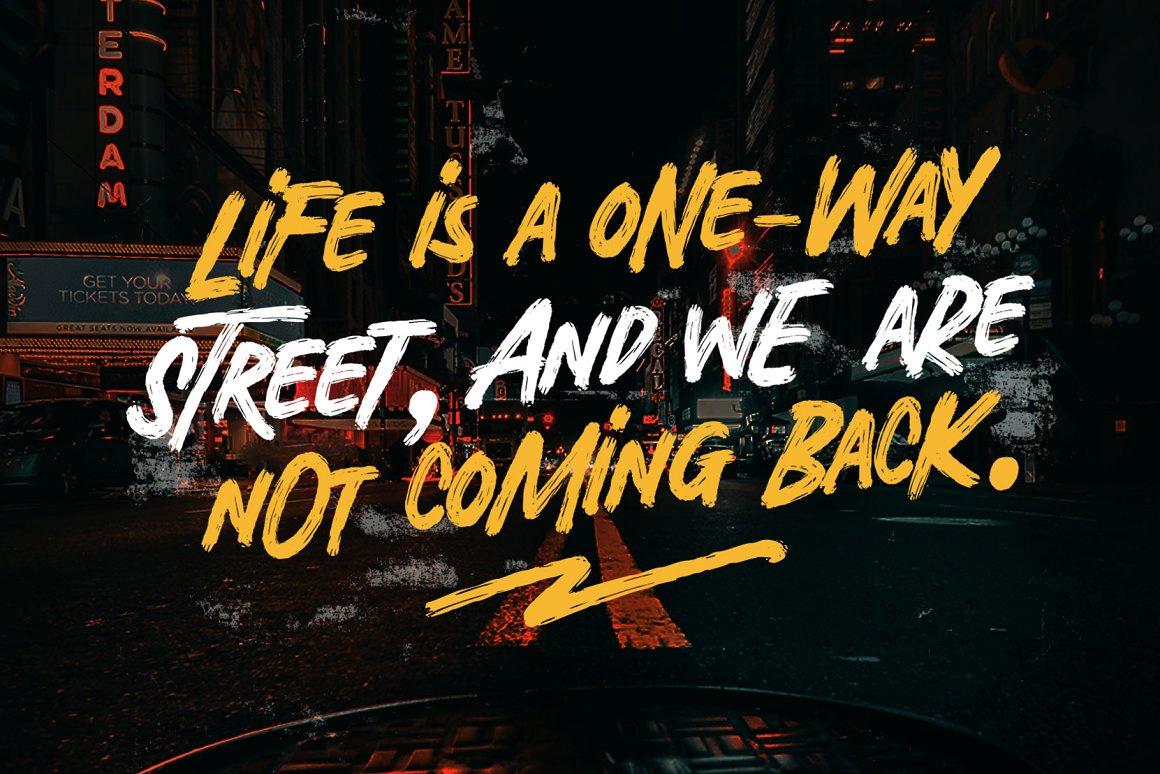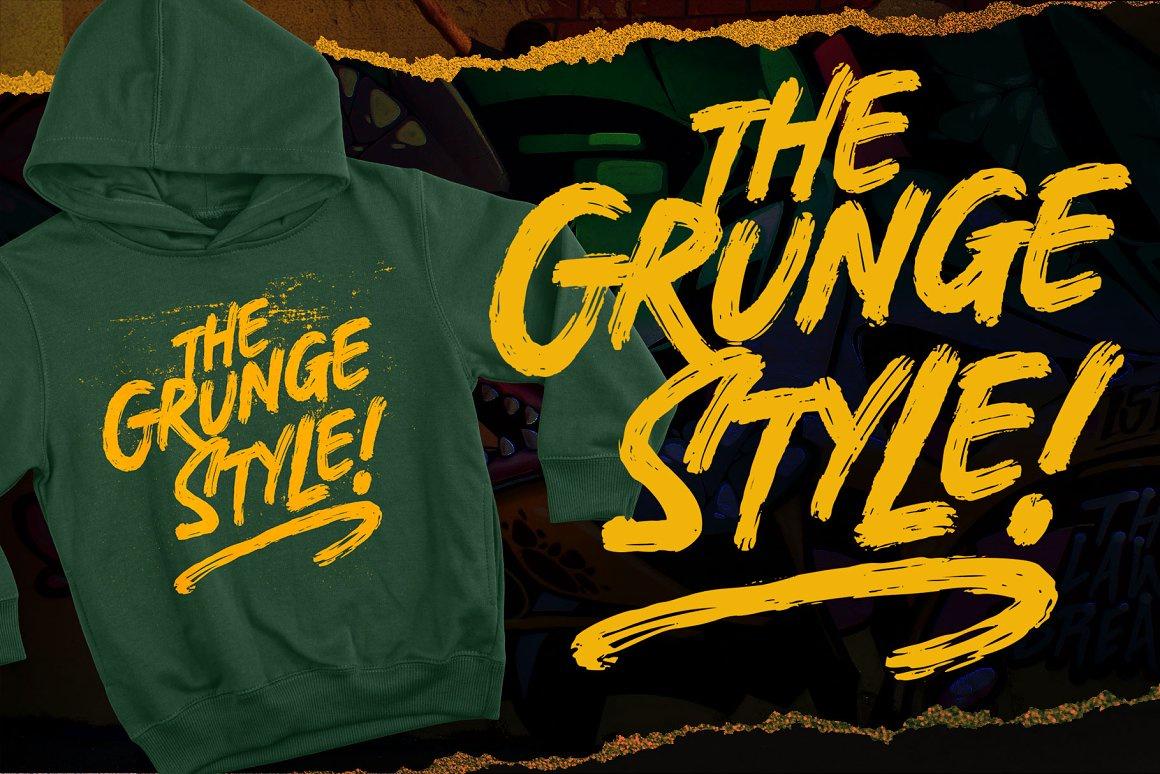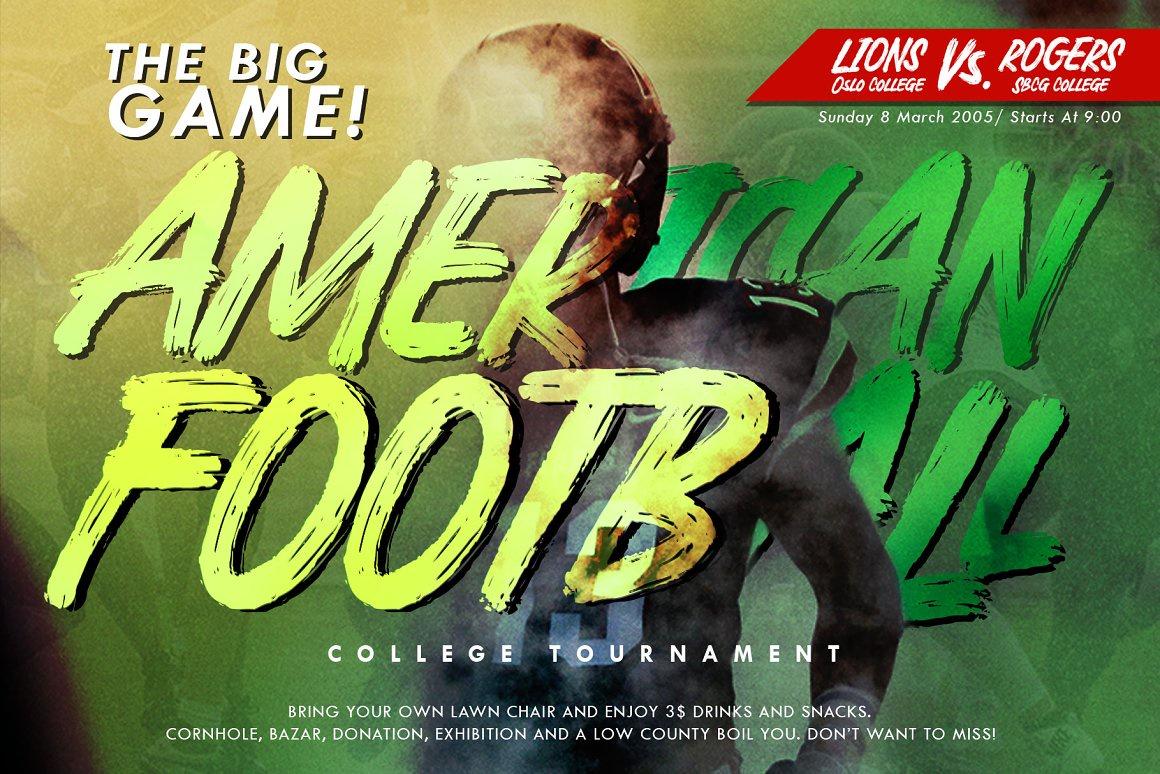
Broken Crush – Brush Font
Broken Crush est une police de pinceau rugueuse créée avec une ligne de pinceau express, conservant les détails et donnant une combinaison accrocheuse entre les majuscules et les petites majuscules, complétée par des alternances et des swashes ! Broken Crush convient à une exposition avec un goût sportif, vibrant et jeune ! C’est un excellent choix d’utiliser cette police pour les logos, les marchandises, les images de marque, les vêtements, les emballages, les citations simples et bien d’autres encore !